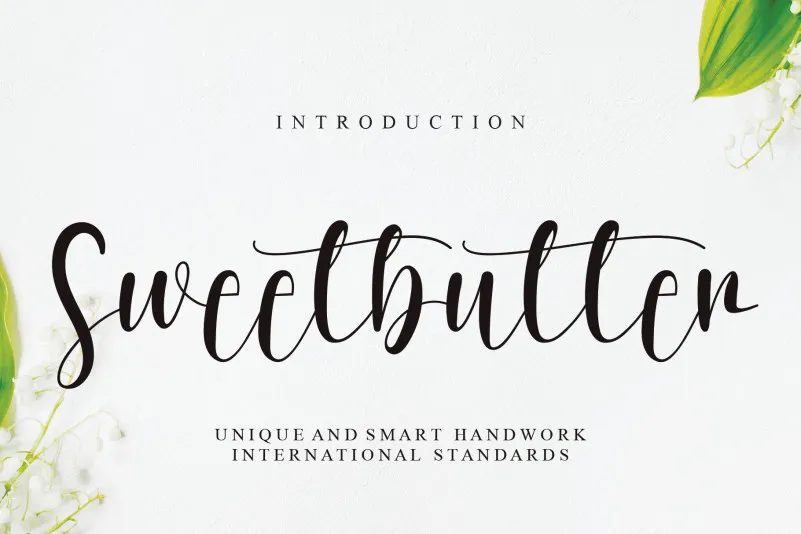
Sweetbutter Font – Download Grátis
A ‘Sweetbutter Font’ é uma elegante fuente cursiva criada pelo designer creativeletter. Seus caracteres delicados e originais se adaptam perfeitamente a uma ampla variedade de projetos que buscam adicionar um toque suave e humano à sua criação. Perfeita para cartazes, design gráfico ou mesmo para decorar seu blog de receitas com aquela pitada doce e elegante dos dias de hoje. Companheira perfeita para qualquer profissional que busca incorporar uma personalidade única em seus trabalhos.